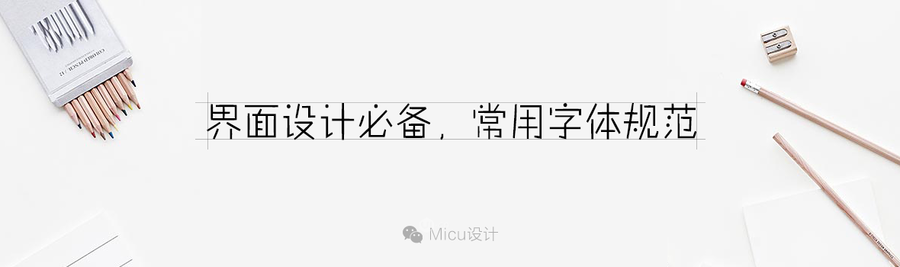
界面设计必备,常用字体规范
这几天有人问我说:“最近看了好多教程,都老高大上了,但是老弟我做不到呀,想学点直接能拿来用的,这个要求过分吗……”
这个,好吧,那就直接说说能用的知识:字体字号。
也许你会说:字体字号?也太Low了吧,这个谁不知道重要呀。
对于这个问题,我想说:会和熟练,是两回事。一个App,不同部分的字体字号你能准确地说出来吗?
很多刚做APP界面的设计师,经常会因为字号,字体颜色,间距而困扰。
拿到设计需求后,开始进行设计,不知道从何去调整界面的字号和行间距等。容易碰到的问题是页面和页面的字号调着调着就大小或颜色不统一了。并且容易导致设计稿反复得修改。设计出来的效果图文字左右间距层次不齐,导致与预期不符等。
这小节我将和大家理一理界面中常用的字体,字号,字体颜色及间距对齐的一些小经验。希望能对大家有些帮助。
一.成也字,败也字
在设计师的职业生涯中,至少一次甚至多次在工作中因为字体不协调栽跟头。在实践的过程中我们会慢慢发现一些规律或者经验规范。接下来我将和大家一起聊聊在界面设计中的那些常规字体的使用规范。
我们常常会听到,这也太LOW了吧!!你能统一一下字体吗?
不明确而繁琐的字体搭配会导致整个画面失调。可以这样说,字体可以成就设计也可以毁掉设计。
问题的关键有:
1.字体样式太多,导致页面杂乱
2.使用的字体不易识别
3.字体样式和内容的气氛或规范不匹配
怎么避免这样的结果发生呢?
通过设计经验可以帮助你做出更好的版式
了解不同平台的常用字体设计规范
在每个项目设计中只使用1-2个字体样式,而在品牌字有明确的规范的情况下,只需要一种字体贯穿全文,通过对字体放大来强调重点文案。字体用的太多,越显得不够专业。
不同的样式的字体,形状或系列最好相同,保证字体风格的一致性。
字体与背景的层次要分明
确保字体样式与色调气氛相匹配
二.界面中文字使用的规则
在不同平台的界面设计中规范的字体会有不同,像移动界面的设计就会有固定的字体样式。网页中会有常用的几个字体,在这我和大家分别介绍一下。
以下是在  72像素/英寸  下的规范
移动端常规字体
IOS:常选择华文黑体或者冬青黑体,尤其是冬青黑体效果最好。
Android
英文字体:Roboto
中文字体:Noto
移动端常用的的字号有哪些呢?
导航主标题字号:40-42px
我一般设计就用40px,偏小的40px字号,显得精致些。
在内文展示中字号大小又是多大呢?
大的正文字号32px,
副文是26px,小字20px
在内文的使用中,根据不同类型的App会有所区别。
像新闻类的APP或文字阅读类的APP更注重文本的阅读便捷性,正文字号36px,会选择性的加粗。
而列表形式、工具化的APP普遍是正文32px,不加粗。副文案26px,小字20px
26px的字号还会用于划分类别的提示文案,因为这样的文字希望用户阅读,但不要抢过主列表信息的引导。
36px的字号还经常运用在页面的大按钮中。为了拉开按钮的层次,同时加强按钮引导性,选用了稍大号的字体。
(见下图中的退出按钮)
大家注意了,在选用字体大小的时候一定要选择偶数的字号,因为在开发界面的时候,字号大小换算是要除以二的。这个详细缘由大家可以网上查询,我就不在这一一的介绍了。
常用字号的大小基本就这几个,根据版式设计需要也会采用异样大小的字号来特殊处理。这种更高的要求设计师的全局把控能力了。
网页端
常用的字号有哪些呢?
网页中文字字号一般都是宋体12px或14px(无状态),大号字体用微软雅黑或黑体。大号字体是18px、20px、26px、30px,一般使用双数字号,单数的字体在显示的时候会有毛边。
常用的字体
1.平平稳稳:微软雅黑/方正中黑
微软雅黑系列:在网页设计中这款字体使用的非常平凡,这款只无论是放大还是缩小,形体都非常的规整舒服。在设计过程中建议多使用雅黑,大标题用加粗字体,正文用常规字体。
方正正中黑系列:中黑系列的字体笔画比较锐利而浑厚,一般运用在标题文字中。但这种字体不适用于正文中,因为边缘相对比较的复杂,文字一多会影响用户的阅读。
2.与时俱进:方正兰亭系列
方正兰亭系列: 个人最推荐的就是这个系类的字体,整个兰亭系列的字体有大黑、准黑、纤黑、超细黑等。因笔画清晰简洁,这个系类的字体就足以满足排版设计的需要。可以通过对这个系列的不同字体进行组合,不仅能保证字体的统一感,还能很好的区分出文本的层次。
3.刚劲有力,运动型:汉仪菱心简/造字工房力黑/造字工房劲黑
在这几个字体中,他们有着共同的特点,字体非常的有力而厚实。基本都是以直线和斜线为主。适合广告和专题使用。在使用这类字体的时候我们可以使用字体倾斜的样式,让文字显得更为活力。在这三种字体中,菱心和造字工房力黑在笔画、拐角的地方采用了圆和圆角。而且笔画也比较的疏松,更多的有些时尚而柔美的气氛。而劲黑这款字体相对更为厚重和方正。这类字体使用在大图中偏多,效果比较突出。
通过自由的书法网站在线生成。在网址中输入文本,再进行选择书法字体样式。通过这种方法我们能很快的找到需要的书法字体。这招非常管用。
和大家简单操作一下毛笔字的使用方法。
将下载下来的字体图片AI转路径,编辑文字。
首先使用在线生成器输入选择好你需要的文字字形,将文字图片拖至AI中。
选中拉入图片,点击[图像描摹]
然后继续点击[扩展]按钮
扩展完毕后,图片已经都变成了路径。
使用魔棒选择颜色就可以将文字的路径提选出来。
最后经过设计后的Banner效果,这就是我经常用的Banner风格,你们也试试吧~
重要提示,怎么找不认识的字体名称?
三.常用字体颜色
字体颜色又有哪些常用的颜色呢?
在界面中的文字分为三个层级,主文、副文、提示文案等。
在白色的背景下,字体的颜色层次其实就是黑、深灰、灰色。
常用的色值是#333333;#666666;#999999
在界面中还经常会用到背景色#eeeeee。
分割线则采用#e5e5e5或#cccccc的颜色值,一个深一些,一个浅一些。这个会更具不同的软件风格采用不同的深浅,由设计自己把控。
设计的时候我们还可以将字体进行变形来达到宣传的目的,这个需要设计师对字体设计有一定的了解。
总之,设计是要有规范,有体系的。使用规范化的设计对产品的延续性非常有帮助,并且保证了产品的独特性和一致性。所以,大家要在设计初期找到风格和规范,这样做出来的界面才会统一一致,在变化的需求中找到定量,调整起来也相对轻松很多。